为设计师设计的 50 多种最佳免费 Monogram 字体
已发表: 2022-06-25您可以在设计中使用的最佳字母组合字体集合。 我们试图列出一些最流行的字母组合字体。
我们知道,一些精美的会标字体可能会让您的口袋难以承受,特别是如果您的预算较低,但有一些最好的免费会标字体可以解决您的问题。
字母组合是大而装饰性的字符,用于为您的请柬、名片、徽标甚至杂志提供适当的吸引力。
因此,您对最佳免费字母组合字体的搜索到此结束,因为我们整理了最佳字体列表。 继续寻找最适合您的。
用于创意设计的顶级会标字体
01.麦克斯韦
谈论最好的免费 Monogram 字体,我们脑海中只有一个名字,那就是 Maxwell。 只有少数其他字体显示出这种多功能性。
您将看到的最简单但最吸引人的设计之一可用于徽标、网页、印刷品、标题等。
02. 会标
由 Woodcutter 创建的 Monogramos 非常适合圆形会标框架,我们都知道它有多受欢迎。 你能想到的第一个印刷品是一个标志。
03. Apex Lake字体
成为艺术的字体有限,Apex Lake Font 就是其中之一。 这种类型的字母组合字体非常适合婚礼请柬、徽标、印刷和 T 恤。 圆形框架和叶子的设计使字体更加优美。
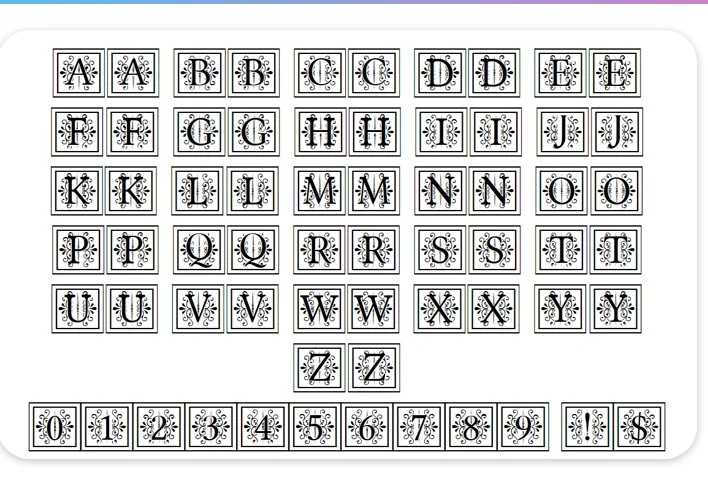
04. 猫 Altgotisch
如果您看一下这种会标字体,您会立即被皇家和独特的设计所吸引。 作为最古老的字体之一,CAT Altgotisch 仍然是一种流行的字体,可用于首字母或广告。
05. 盖茨比派对
经典的魅力,可能非常适合 Gatsby 主题场合,Gatsby 的派对是一个干净的设计。 简约的外观和简单的方法可以作为您想要的正确字体。
06. 塔米拉
大胆的设计永远不会过时,不是吗? Tamira 有一个大胆的设计,但对眼睛非常舒缓。 读者在阅读此字体时不会感到任何困难。 此外,该字体有 4 种粗细可供选择。
07. Monogram Rounded
寻找一种能在一秒钟内吸引读者眼球的字体? Monogram Rounded 以其独特的设计一定会给人留下深刻的印象。
08. 龙虾
由 Romening Silva 创造的大胆设计,Lobster 是最好的免费字母组合字体之一。 这种字体以其多功能性而闻名,因为它可以在任何地方使用,例如徽标、标题和杂志。
09. 圆形会标
最好的免费圆形字母组合字体之一,圆形字母组合具有独特的设计,可以成为首字母的完美选择。 它没有任何字母组合框架,但圆形结构提供三个选项 - 左、中和右
10. Janda 时尚会标
顾名思义,如果这种字母组合字体不缺少的一件事就是样式。 以下是设计师 Kimberly Geswein 的建议,使用小写字母作为侧首字母,大写字母作为中心首字母。
11. Finegramos字体
在设计项目时,您需要有免费的脚本字母组合字体。 Finegramos 字体可能是这一领域中最好的字体。 无论是图像还是徽标,都会增加吸引力。
12.谢弗
如果您正在寻找一种能够为您的项目带来复古外观的字母组合字体,那么 Schaeffer 将是您的完美选择。 平行线是如此有趣,它会给读者留下美好的印象。
13. Zilap Monograma
由 LJ Design Studios 创建的 Zilap Monograma 将是复古和现代外观的理想组合。 这种会标字体非常适合徽标甚至首字母。
14. 艾利夫
就像 Alex Lake 字体一样,Alyfe 是一种在设计中使用自然元素的字母组合字体。 如果我们必须设计一张有吸引力且浪漫的贺卡,Alyfe 将是完美的选择。
15.反驳
这种字体最好的一点是全大写结构使其极具吸引力和多功能性。 大胆的笔触和经典的触感让您轻松完成运动主题项目。
16. KG 现代字母组合
Kimberly Geswein 设计的另一件杰作,KG Modern Monogram 让您意识到简单干净的设计如何影响吸引力。
为获得最佳效果,请在小写字符之间键入大写字符。
17. 字母组合 KK
这种引人注目的草书字体是可用的最好的免费字母组合字体之一。 卷曲的字母提供优雅,简约的设计非常适合大写字母。
18. 卡斯隆花饰
斜体和装饰曲线可能是使其与会标字体不同的最佳特征。 最重要的是,Caslon Swash 在字母之间有足够的间距,使其更具吸引力。
19. Simpla 字体
吸引读者的眼球并立即产生影响是您的主要目标吗? Simpla 字体花卉图案是正确的字母组合字体。 厚波浪的设计会催眠你的读者阅读标题和标志。
20.苦
Bitter 是一种以简洁着称的字母组合字体。 读者在阅读此字体时不会有任何问题。 最重要的是,Bitter 有 4 种字体粗细可供选择——常规、斜体、粗体和粗斜体。
21. 海狸
这种字体的粗体可以使文本立即看起来很有吸引力。 它是一种免费的字母组合字体,可用于书写首字母、标题、T 恤、杂志和广告。
22. 杰里奥·法索拉达
Gelio Fasolada 受到希腊书法的启发,由 Cumberland 字体作品设计。 关于这种设计,您会注意到的一件事是,所有字母都以不同的角度设计,采用大胆的方法,使其成为字母组合的理想选择。
23. 巴黎人
如果它简单明了的外观更能吸引你,那么 Parisish 将是你的会标的完美选择。 设计师 George Williams 确保此设计不涉及任何复杂性。
24. MTF Base Leafy 字体
装饰字母组合字体有自己的结构和重要性。 它们带来了设计的独特性。 MTF Base Leafy 字体具有大胆的外观和自然元素,可能是您单个字母组合的完美设计。
25.罗伊克罗夫特
另一种可以用作单个字母组合的免费字母组合字体是 Roycroft。 全部大写的野兽看起来非常适合您项目的首字母。 皇家和经典的外观会给读者留下深刻的印象。
26. 形态学
现代外观和大胆的边缘使 Morphectics 成为最好的免费字母组合之一。 这种字体的高对比度方法使其成为希望其文本脱颖而出的人们的最爱。
27. Konanur 字体
如果您不想要被确定形状覆盖的字母组合字体,Konanur Font 是您的完美字体。
框架的设计独特,充满曲线。 使用此字体,您的姓名首字母和徽标将看起来更具吸引力。
28. 舒适
Comfortaa 由 Joan Aakerlund 设计,是一种相当简单的字母组合字体。 Comfortaa 有 3 种字体粗细可供选择 - 浅色、常规和粗体。 它是大胆和纤薄设计的完美结合。
29. 西加
Chyga 由 Eva Barabasne Olasz 设计,看起来像一个可以轻松玩的字母组合字体。 字符边缘的不规则卷发使这种字体非常吸引人。
30. 伊丽莎白时代的缩写
恐怖故事中的蜡烛可能是对这种字母组合字体的完美描述。 Elizabethan Initials 是最古老的字母组合字体之一。 该字体具有独特的设计,非常适合万圣节和其他类似活动。
31. 排序传真
如果您使用 Sortefax,您的字母组合将会脱颖而出。 这种字体最大的特点是阴影效果。 这种时尚的字体也可以在设计徽标、T 恤和标题时使用。 这种字体的设计重点是可读性。
32.洛夫格拉姆斯
我们不能沉迷于形状的字母组合字体。 由 Woodcutter 设计的 Lovegrammos 基本上是一个设计成心形的字母。 大胆的外观将使您的字母组合脱颖而出。
33. 时尚
块状字母组合字体永远不会过时,我们相信 Vogue 也是如此。 简约简约的设计非常适合杂志。
它让你意识到,有时你不需要有创意来吸引读者的注意力。
34.康斯坦茨
另一个免费的脚本字母组合,Constanze 列出了我们最好的免费字母组合字体。 足够的间距,粗细的混合以及边缘的曲线是使它如此吸引人的特征。
35. 瓷器
大多数时候,额外的曲线和重斜体的方法往往会降低字体的吸引力,但对于这种字母组合字体来说并非如此。 瓷器的大胆方法以及曲线使其成为字母组合的理想选择。
36.字母组合工具箱
边缘粗糙的干净设计使这款字母组合字体如此特别。 中世纪风格可以完美地在您的文本中营造复古魅力。
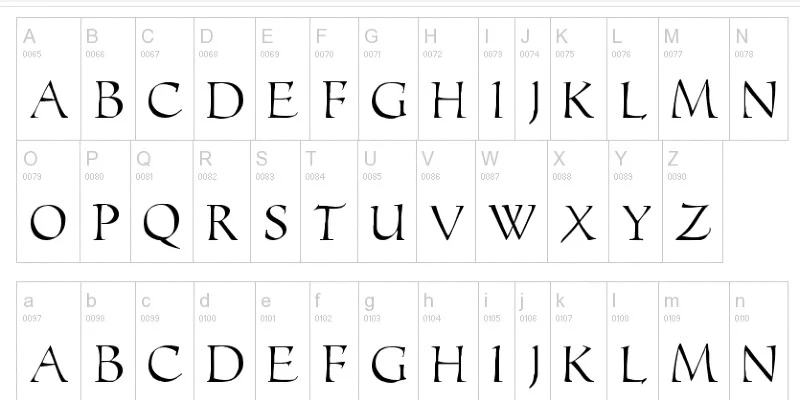
37.恋人争吵
如果你曾经想过恋人的争吵会是什么样子,那么设计的曲线会让你知道它变得多么复杂。 这种字体的美在于设计的斜体卷发。
38. 兰兹当
Landsdown 由 Paul Floyd 设计,是一种强烈而简单的字母组合字体,其灵感来自中世纪时期。 它有大写字母、小写字母,甚至一些数字。 为了充分利用它,在两个小写字母中间使用一个大写字母。
39.更高的进化
谈论最好的无衬线字母组合字体之一,Taller Evolution,它强烈的垂直强调会给你九十年代的怀旧之情。 干净大胆的设计非常适合您的字母组合、首字母和徽标。
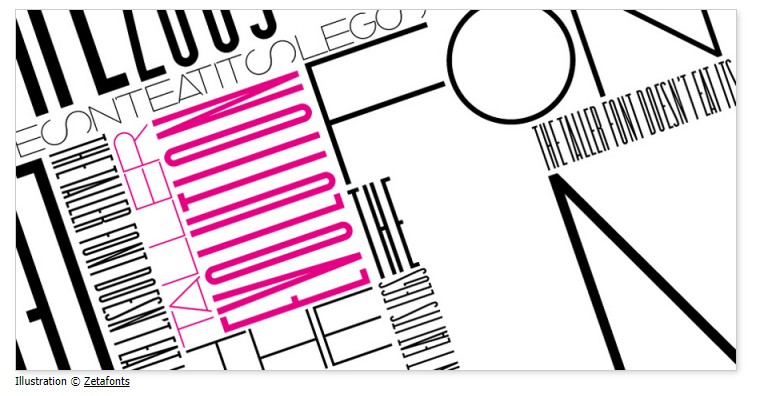
40. Cursif
Cursif 漂亮的脚本字体由 Christophe Beaurmale 设计,大胆而舒缓眼睛。 间距和曲线使它更加特别。
您不必担心包,因为它包括大写、小写、数字和符号。
41. Ecuyer Dax
如果您正在寻找细线和简洁,Ecuyer Dax 将简化您的字体的存在。 粗体字母内的水平线使其对读者很有吸引力。
42. 以上
如果你仔细观察,你会发现边缘有点粗糙,这使得 Above 成为最好的字母组合字体之一。 这种字体适用于标志、标题,甚至杂志。
43.雾灯
Foglighten 的艺术笔触将非常适合您的皇室主题场合。
不太粗的线条末端的美丽卷发非常适合制作徽标、字母组合、首字母和杂志。
44. 目的
一种大胆的方法将是在您的文本中发表声明的理想选择。 这种棱角分明的简单设计提供小写和大写字母、数字和符号。
45. 生锈的垂耳兔
Rasty Lop 字体简单而纤薄,仅在大写组中可用。 细纹永远不会过火。 一种无衬线字体,非常适合您的现代字母组合。
46.斯金兹
我们称这种字体为“来自未来的字体”,你无法从它的设计中理解这一点。 在未来的日子里,字母之间的粗细和间距肯定会变得更加流行。
47. 香格里拉
在中国城灵感的帮助下,香格里拉的极简主义风格将令人惊叹。 在包中,您将获得大写字母、数字和大量符号。
48. 卡灵顿
这个字体会响吗? 您可能已经在一些大品牌中看到过这种字体。 这种字体是粗体、斜体的,卷发就像蛋糕上的樱桃。
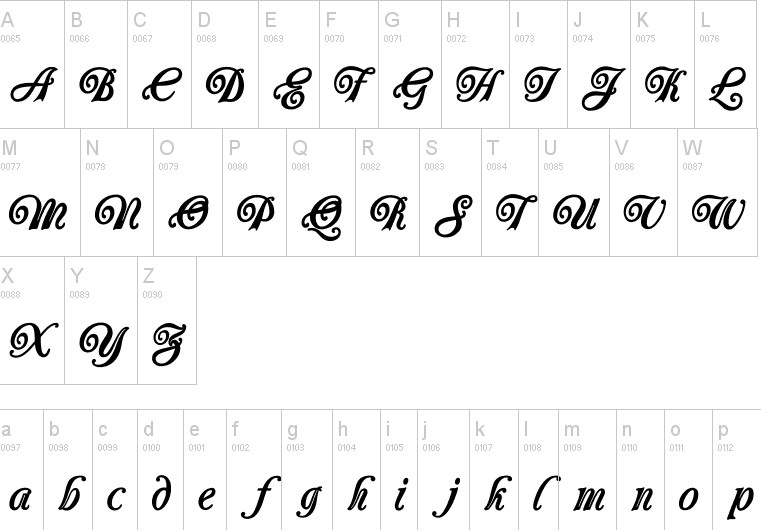
49. 伊萨德佐克
镂空的字母框架,加上阴影效果,使 Itadzoke 成为该系列中精美的字母组合字体。 这种字体令人耳目一新,易于阅读。 您看到这种字体的次数越多,您就越喜欢它的笔触。
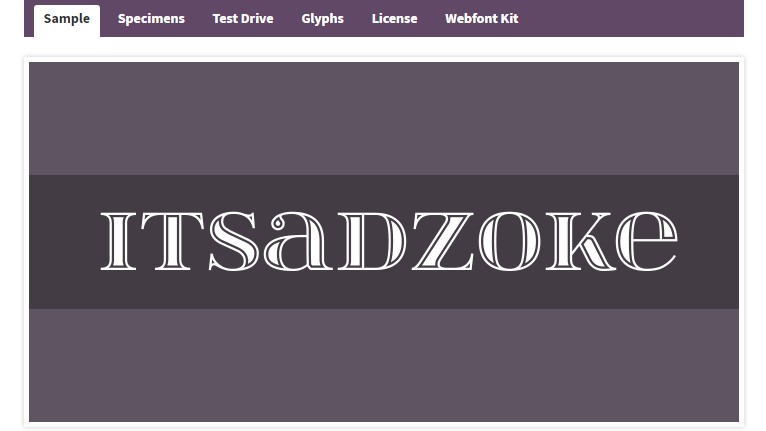
50. 中子
列表中的最后一个,Neutronium 的灵感来自科幻主题。 如果您想让您的字母组合具有现代感和未来感,Neutronium 将是一个理想的选择。
51.黑色字母组合字体
BLACK 是一款深色且有吸引力的字母组合字体设计,具有完全独特的风格。 具有独特尺寸的字体将使任何项目看起来都很有吸引力。
这种字体是标志设计、字母组合设计、品牌、营销图形、横幅或任何其他创意设计的绝佳选择。
我们汇总了您无需付费的顶级会标字体列表。
其中一些具有现代感,而另一些将为您的文本提供现代和皇家的外观。